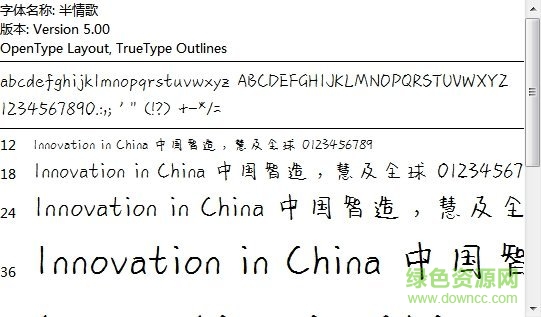
半情歌体
半情歌是一款有着清新笔触和柔软字迹的手写字体,落笔从容而有神,让你感受不一样的个性魅力,喜欢的朋友就来绿色资源网下载收藏吧!
半情歌字体简介
再小的空间和时间,再远的距离或永远,都抑制不住我内心暗暗生长的小思念。
半情歌体是一款充满倾诉的情书字体,笔尖流动着数不清的缱绻情丝,撩拨你的拳拳心意,让设计更有人性化,让包装设计、海报设计更有独特呈现。